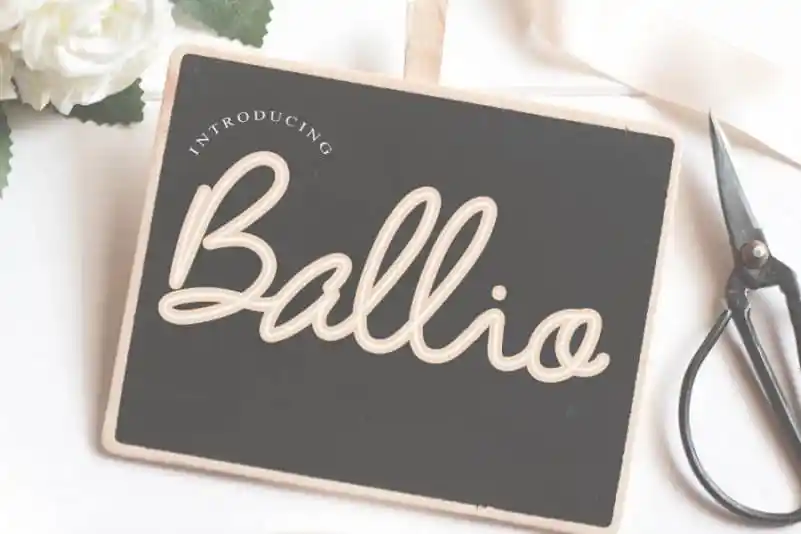
Ballio Handwritten Font – Fonte Grátis
Ballio Handwritten Font
A fonte Ballio Handwritten é uma escolha ideal para designers que procuram uma mão escrita natural e simples. Este original visual se destaca por sua leveza, tornando-a perfeita para várias aplicações de design criativas. Através do Ballio Handwritten Font, você pode criar desde cartões de visita até cabeçalhos atraentes, ou até mesmo adicionar um toque único à identidade visual de seus produtos de papelaria. Com sua aparência natural e intuitiva, esta fonte se adequa perfeitamente para qualquer projeto que deseje transmitir uma mensagem única e pessoal, tornando-a uma ótima opção para designers brasileiros buscando uma mistura suave entre a tecnologia moderna e um toque de personalidade autêntica.